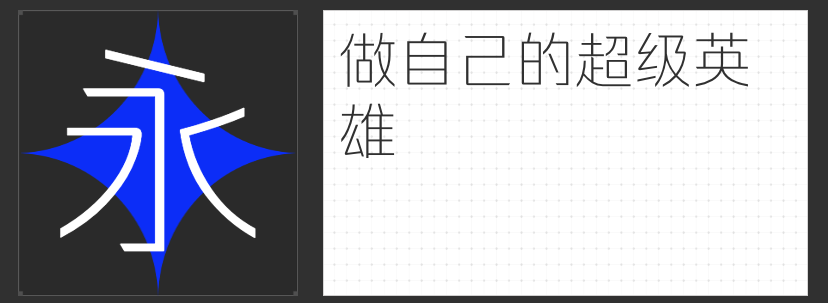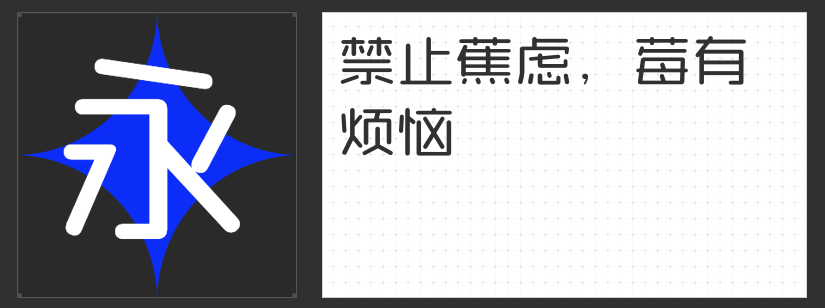
游戏设计内嵌字体精选:四款字体赋能沉浸式体验
在游戏设计中,字体不仅是信息传递的载体,更是构建世界观、强化氛围的关键元素。励字造梦字库推出的四款字体,以独特的设计语言适配不同风格的游戏场景,为开发者提供多元化的视觉解决方案。
一、励字圆梦简 常规
这款字体以直线笔画为基础,通过竖折结构替代传统弧线,形成简洁明快的几何形态。笔画起收处融入圆体自然弧度,中宫松散、外圆内方的设计,既保留了科技感的锐利,又通过柔和的边角处理降低视觉疲劳。其字形结构适配科幻类游戏UI设计,尤其在星际航行、虚拟现实等场景中,能通过圆角与直线的对比强化未来感,同时保持文字在动态画面中的清晰可读性。
二、励字志向黑简 超粗
作为圆体与黑体的融合体,这款字体在笔画拐角处采用外圆角处理,既延续了黑体的稳重结构,又通过圆弧元素注入灵动气质。超粗字重使其在战斗场景、技能特效等高强度视觉输出中脱颖而出,例如在角色释放大招时,粗壮的字体与光影效果叠加,能瞬间强化冲击力。其屏显适配性经过优化,即使在小尺寸移动端也能保持笔画完整性。
三、励字超级勇士简 特细
以特细笔画构建的黑体字,通过匀称的中宫布局与清爽的笔画线条,形成高度通用的视觉语言。这款字体适用于需要大量信息展示的场景,如任务说明、道具描述等界面。其极简设计风格与赛博朋克、解谜类游戏高度契合,细笔画在霓虹光效或暗黑背景中能形成精致的视觉层次,同时避免文字喧宾夺主。
四、励字书宋简繁
正宗老宋体风格赋予这款字体典雅大气的气质,横轻竖重的结构与均匀的布白,使其成为历史题材、武侠类游戏的首选。在剧情对话、书信道具等叙事场景中,宋体的工整感能强化文字的仪式感。
这四款字体通过差异化设计,覆盖了从科技未来到古典东方、从高强度战斗到细腻叙事的全场景需求。开发者可根据游戏世界观选择核心字体,并通过字重、大小、颜色的动态调整,构建层次分明的视觉叙事体系,最终实现信息传递与情感共鸣的双重目标。